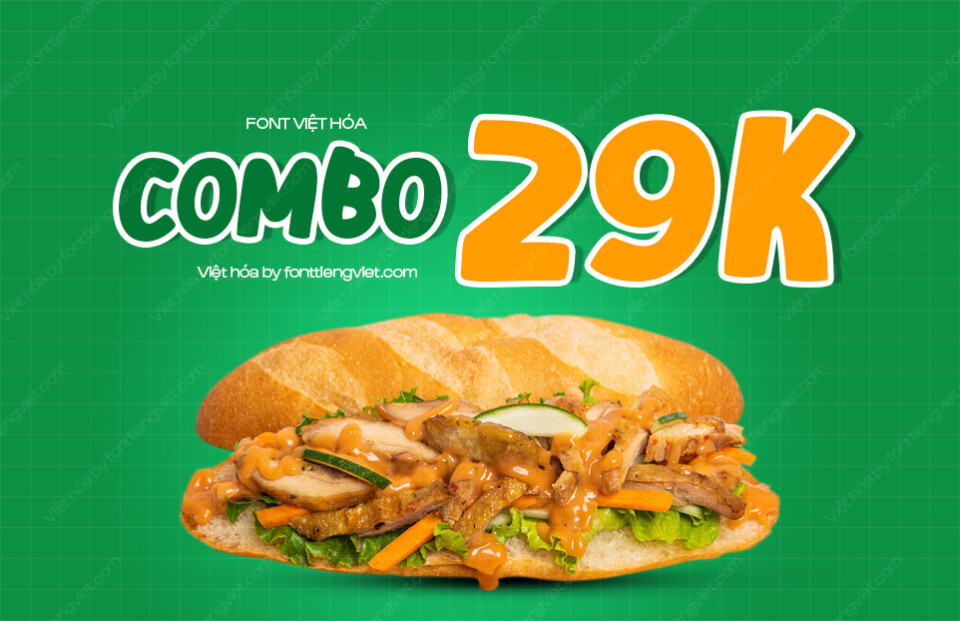
Font Việt hóa 1FTV VIP Vanily – Lựa chọn hoàn hảo cho thiết kế sáng tạo
Giới thiệu về Font Việt hóa 1FTV VIP Vanily
Trong thế giới thiết kế đồ họa hiện đại, việc tìm kiếm một bộ Font Chữ vừa mang nét tinh tế, vừa hỗ trợ đầy đủ tiếng Việt là điều vô cùng quan trọng. Font Việt hóa 1FTV VIP Vanily nổi lên như một giải pháp hàng đầu dành cho các nhà sáng tạo nội dung và học sinh, sinh viên tại Việt Nam. Đây là bộ phông chữ được tinh chỉnh kỹ lưỡng, giúp loại bỏ hoàn toàn các lỗi hiển thị dấu tiếng Việt phổ biến, mang lại sự mượt mà và chuyên nghiệp cho mọi bản thảo hay ấn phẩm truyền thông trường học.
Những đặc điểm nổi bật của bộ font này
Phong cách thiết kế hiện đại và thanh lịch
Font Việt hóa 1FTV VIP Vanily sở hữu đường nét thanh thoát, hiện đại nhưng không kém phần mềm mại. Kiểu dáng này rất phù hợp để trình bày các bài tiểu luận, làm thiệp chúc mừng hoặc thiết kế slide bài giảng cho thầy cô giáo. Sự kết hợp giữa các nét dày và mỏng tạo nên một nhịp điệu thị giác ấn tượng, giúp người xem dễ dàng tiếp nhận thông tin một cách tự nhiên nhất.
Khả năng ứng dụng đa dạng trong học tập
Với bộ Font Việt hóa 1FTV VIP Vanily, bạn có thể tự tin áp dụng vào các dự án từ đơn giản đến phức tạp. Từ việc trang trí bảng tin lớp học đến tạo logo cho các câu lạc bộ ngoại khóa, bộ phông này đều đáp ứng xuất sắc. Đặc biệt, tính năng hiển thị sắc nét trên cả màn hình điện tử và bản in giấy giúp người dùng yên tâm về chất lượng đầu ra của sản phẩm thiết kế.